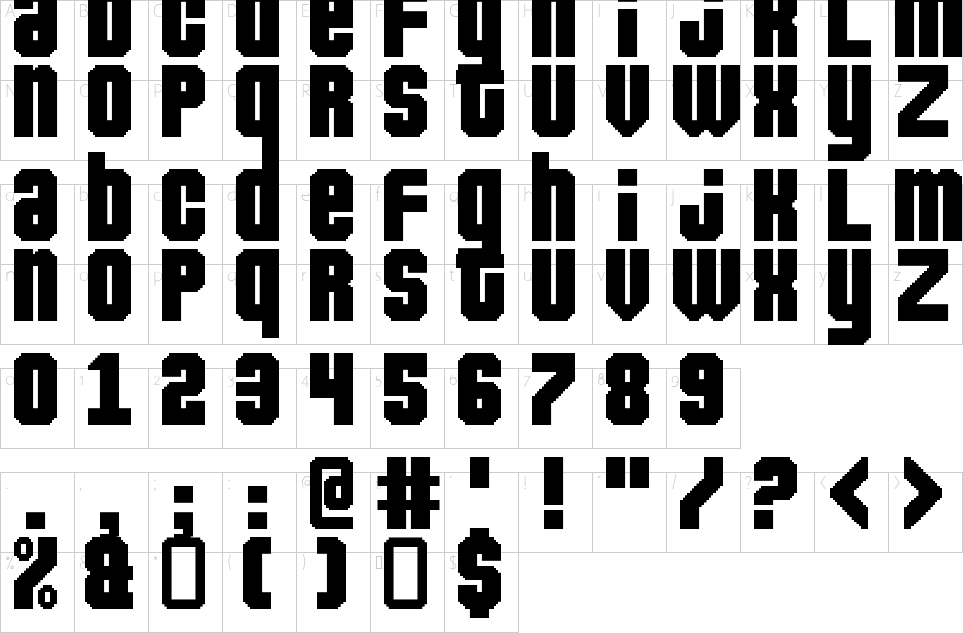
A Pixeldown é uma fonte de design minimalista e moderno, perfeitamente adequada para aplicativos digitais e websites. Criada pelo designer Vasily Draigo, conhecido como Daymarius, ela apresenta um visual limpo e versátil, adequado para diversos usos. Esta fonte foi projetada para oferecer uma experiência de leitura agradável, especialmente em grandes tamanhos de texto. Com uma ampla gama de caracteres e facilidade de uso, Pixeldown é uma ótima escolha para designers que buscam uma fonte moderna e versátil. Embora não tenha sido atualizada recentemente, a Pixeldown continua sendo popular e foi baixada mais de 12.139 vezes, demonstrando seu valor e qualidade. Seja para aplicativos, websites ou documentos, a Pixeldown é uma fonte de grama alta para qualquer designer.